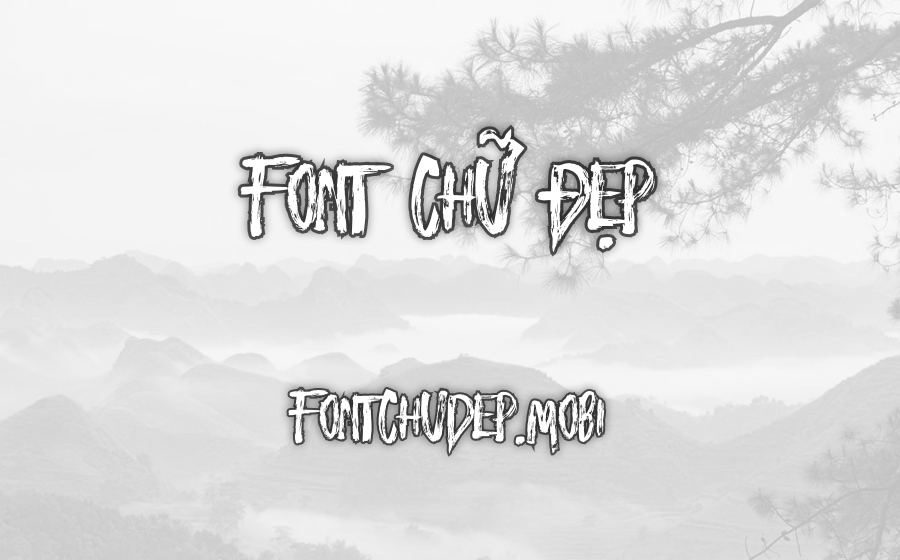
Font LNTH Zombies Việt Hóa
LNTH Zombies Regular
Font Zombies đã tạo ra một làn sóng mới trong thế giới font chữ nhờ vào thiết kế độc đáo mang phong cách kinh dị. Với những nét chữ méo mó và gồ ghề, font này thực sự khiến người nhìn cảm thấy rùng rợn và ấn tượng. Không ngạc nhiên khi nó trở thành lựa chọn phổ biến cho các thiết kế liên quan đến Halloween, truyện tranh kinh dị, poster phim kinh dị, hay bất kỳ sự kiện nào muốn tạo không khí bí ẩn và ma quái.
Một trong những điểm nổi bật của Font Zombies chính là đường nét thô ráp, độ dày trung bình và sự ngẫu hứng trong từng ký tự, giúp tạo ra sức hút mạnh mẽ, đặc biệt khi dùng cho các tiêu đề lớn và các thiết kế huyền bí.
Xét về thiết kế, Zombies sở hữu các đường nét méo mó và cấu trúc không đồng đều, từ đó mang lại cảm giác kỳ quái vô cùng đặc biệt. Font chữ này không chỉ phát huy tác dụng tốt trong tiêu đề lớn, banner hoặc áp phích, mà còn có sức hút mạnh mẽ ở các sản phẩm truyền thông đòi hỏi sự độc đáo và phá cách.
Sự ứng dụng rộng rãi của Font Zombies trong các sự kiện như Halloween, lễ hội kinh dị, cùng nhiều ngành nghề như quảng cáo, thiết kế đồ hoạ, và trang trí lễ hội đã khẳng định rằng đây là một font không thể thiếu cho bất kỳ ai muốn tạo nên ấn tượng mạnh mẽ và bí ẩn trong tác phẩm của mình.